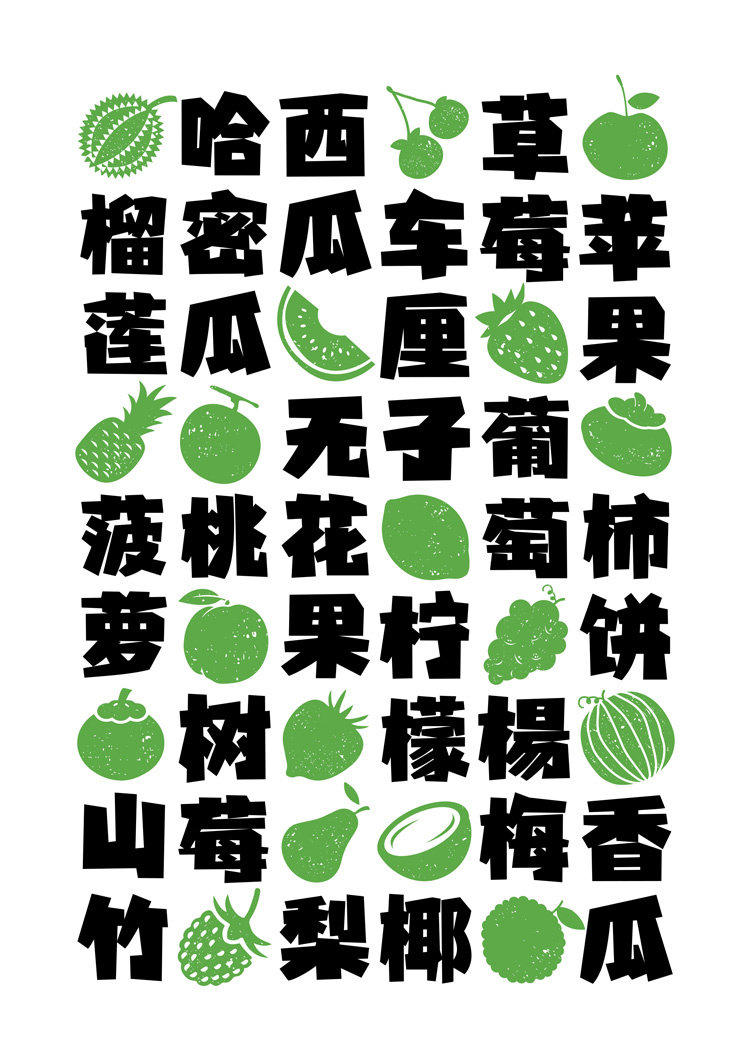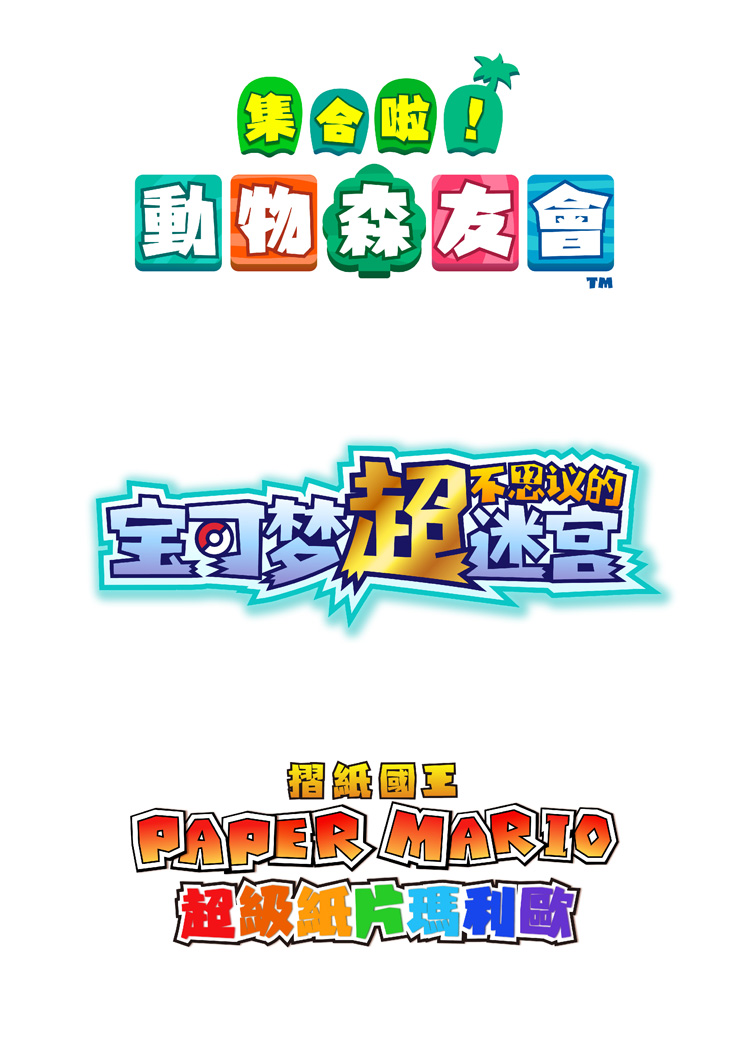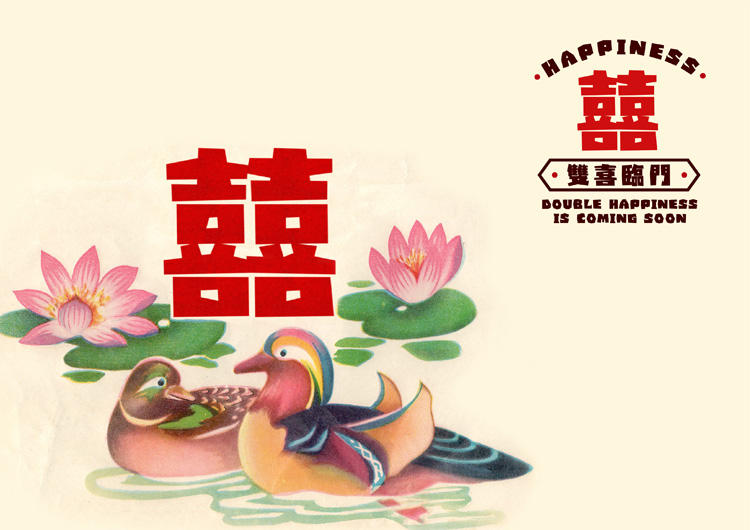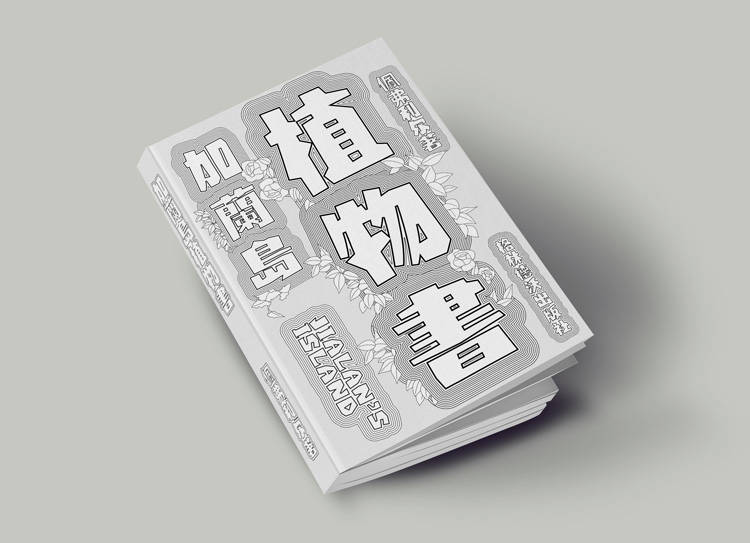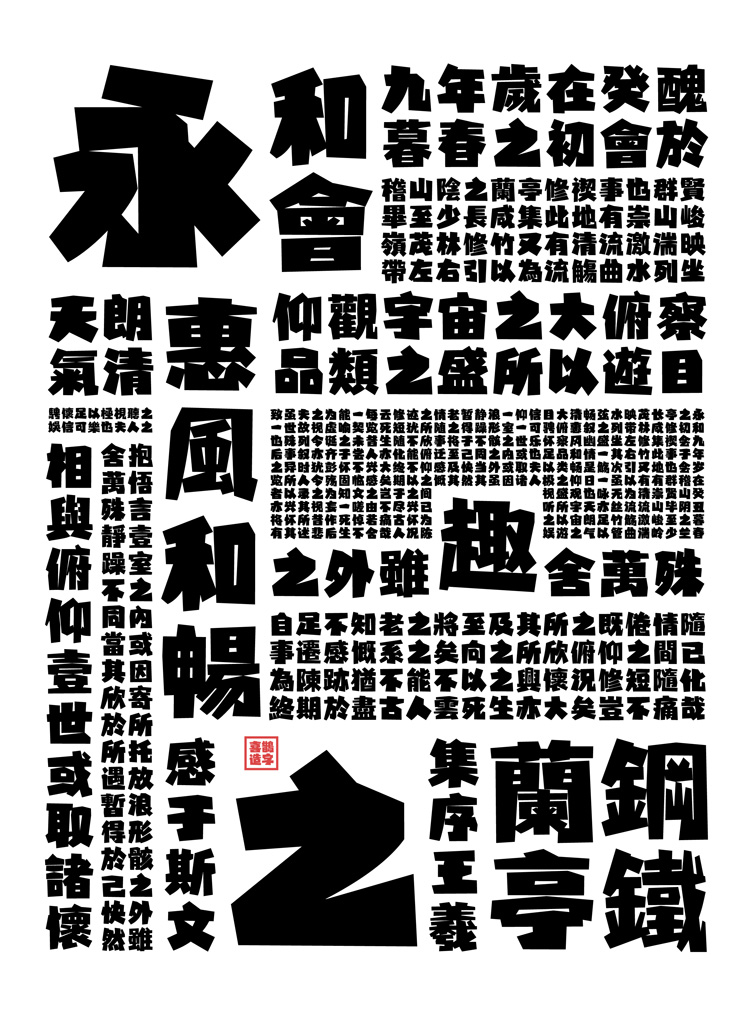
喜鹊造字新字 | 喜鹊直率体-现代综艺风格
字体介绍:不管不顾、大刀阔斧地用线与面塑构造出一笔笔大面积的汉字笔画,宽厚的堆积带给人畅爽的感觉、憨直的印象。并于结字时率性而为,直抒胸臆。故直率体由此得名。每个字如同图形一样,留给人更多的想象空间。整体对比强烈 质朴纯真。单字醒目,可品。组字有趣,可玩味。
适用于:此字形适用海报大标题,适合现代综艺风格标题文字需求,适合动漫与游戏标题、淳朴产品包装与品牌形象 以及复古品牌、广告标题、创意产品展示等等。